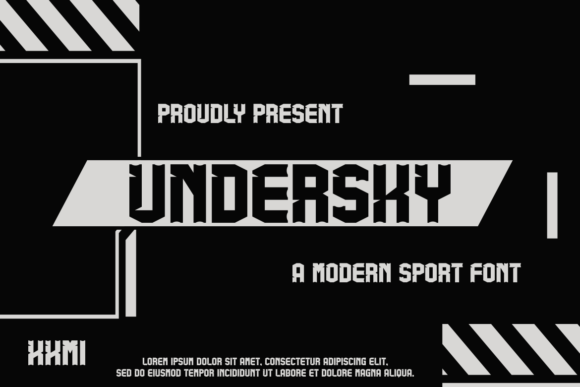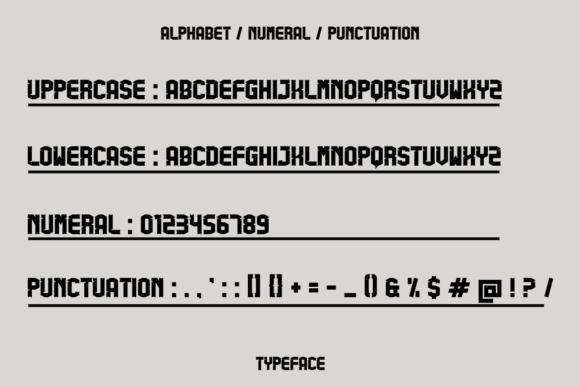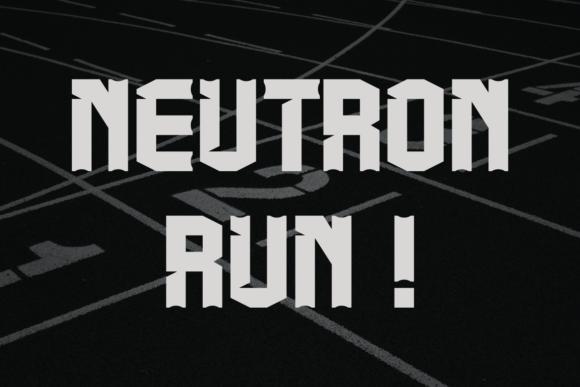
فونت Undersky انگلیسی
دانلود فونت Undersky انگلیسی Font آندر اسکای |
| ⭐ توضیحات | معرفی محصول جدید **فونت UNDERSKY** – فونت مدرن
**فونت UNDERSKY** – فونت مدرن یک فونت نمایشگر برجسته و معتبر است. این فونت برای هر پروژه برندسازی مانند لوگو، طراحی قالب، esport و بسیاری موارد دیگر مناسب است. برجسته در طیف گسترده ای از زمینه ها. |